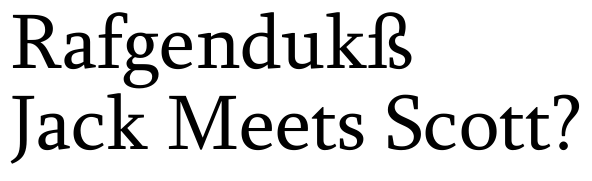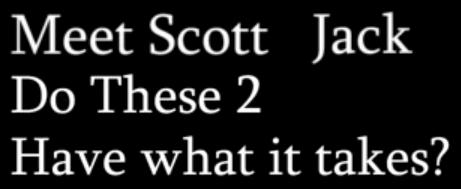
Der Ascender (Liberation) Serif ähnliche Antiqua
Hmm ... auf den ersten Blick wirkt sie total vertraut – nach dem Zweiten merk ich aber auch, dass ich keine Ahnung hab. Woher stammt denn das Bild?
Mir ging’s genauso – ich dachte zuerst auch: Die sieht aus, als ob ich sie kennen müßte!
Aus einem im Netz gefundenen Film. Ich werde mal versuchen, herauszufinden, wo der ursprünglich herkommt.
hast du damit erfolg gehabt? der fall interessiert mich immer noch. ich bin in der zwischenzeit auf zwei schriften gestoßen, die dem muster mehr oder weniger stark ähneln:
loreto von pablo cosgaya und eduardo tunni
charlotte von michael gills
›close, but no cigar‹ würde ich mal sagen.
Das Gefühl ,,wirkt vertraut'' war eine Scheinsicherheit. Bei mir kam ein ähnliches Gefühl hoch. Aber das lautete: ,,Schriften dieser Art sieht man täglich: beliebig, gefällig und austauchbar.'' Der zweite Gedanken: ,,Wenn ich die schon mal gesehen habe: Könnte ich mich überhaupt erinnern?''
Die Schrift ist IMHO etwas wie die Charter, aber das Fragezeichen passt nicht. Das passt bei der ATF-Antique, aber dann passt das J nicht. Bei ähnliche Schriften zur Charter und/oder ATF-Antique findet man noch einige weitere ähnliche Schriften. Aber diese haben fast immer ein falsches J (ohne Unterlänge) und häufig ein unpassendes Fragezeichen. Als Notlösung würde ich die ATF-Antique (AKA Egyptian 505) ansehen: http://www.identifont.com/show?6NM
Was für ein Zufall! Ich konnte den Film zurückverfolgen — und gerade eben habe ich auch erfahren, daß es sich um die Sylfaen handelt. (Trotzdem vielen Dank, Jens, für die Auflösung!)
Und sie befand sich die ganze Zeit auf meinem Rechner … :lol:
Die Schrift wurde von John Hudson und W. Ross Mills von Tiro Typeworks und Geraldine Wade von Monotype gestaltet. Sie enthält lateinische, kyrillische, griechische, armenische, georgische, äthiopische und IPA-Zeichen sowie Kapitälchen. (Windows liegt nur eine eingeschränkte Version bei.)
Leider gibt's aber nur einen Schnitt, keine Kursive oder Fette. :(
Thierry, vielen Dank für den Hinweis auf Loreto und Charlotte. Die sind ja echt ziemlich ähnlich. (Die Sylfaen gefällt mir trotzdem einen Tick besser.) Die Charlotte hat sogar ne passende Sans. Vielleicht kauf ich mir eine der beiden!
ja, wirklich schade. ich ?nde die sylfaen auch interessant, und die zeichenbelegung des regular-schnittes ist ziemlich üppig. die charlotte ist aber auch nicht schlecht. berichte mal von deinen erfahrungen, wenn du dir eine von den beiden tatsächlich gekauft hast.
bevor ich es vergesse: eine weitere ähnliche mit passender sans ist mir aufgefallen, nämlich die karmina von veronika burian und josé scaglione. etwas kantiger, aber dafür gut ausgebaut:
und dann war da noch die (wie ich ?nde: etwas schwächere) azuza von jim parkinson: